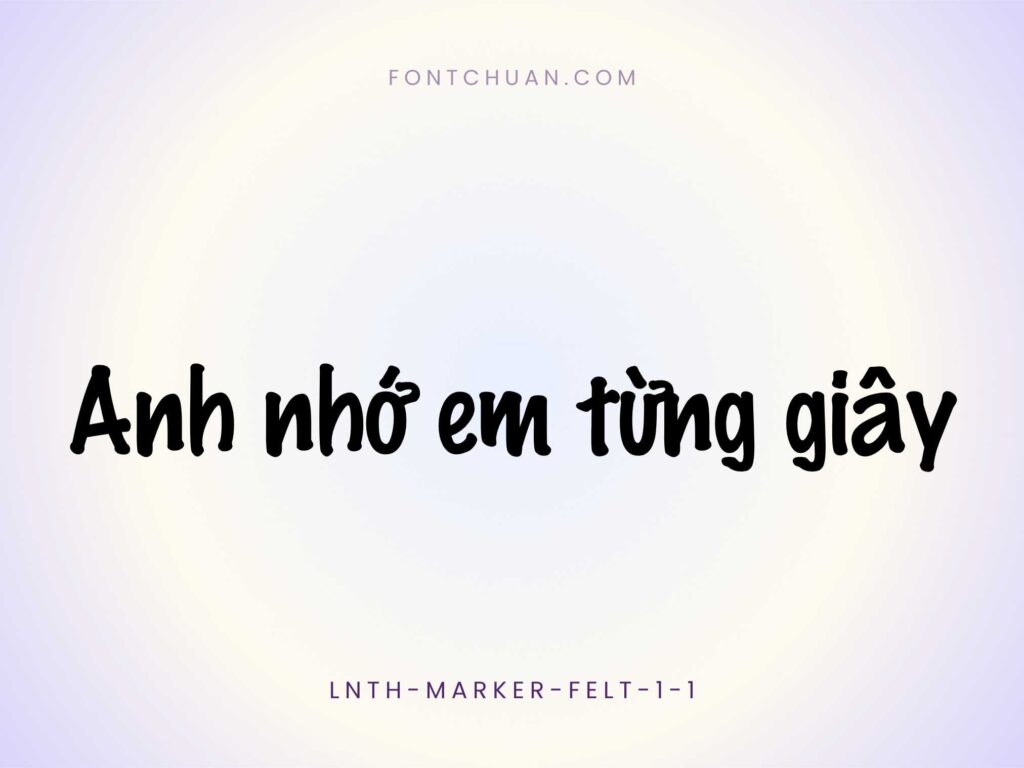
Font LNTH Marker Felt Việt Hóa
Font Marker Felt là một font chữ viết tay mang phong cách năng động, được thiết kế mô phỏng các nét bút dạ viết trên giấy. Với đường nét đậm, hơi thô nhưng đầy cá tính, font này rất phù hợp cho các thiết kế mang tính sáng tạo, trẻ trung, hoặc các nội dung cần sự nổi bật, vui tươi. Marker Felt thường được sử dụng trong thiết kế tiêu đề, quảng cáo, hoặc các ấn phẩm truyền thông sáng tạo
Phiên bản này đã được Việt hóa bởi LNTH, hỗ trợ đầy đủ tiếng Việt cùng hơn 50 ngôn ngữ khác, giúp người dùng dễ dàng ứng dụng trong thiết kế quốc tế. Font Marker Felt được các thành viên Font Chuẩn sưu tầm và đăng tải nhằm cung cấp một lựa chọn phù hợp cho những ai muốn sử dụng kiểu chữ năng động, phá cách
Về đặc điểm thiết kế, Marker Felt có độ dày lớn, đường nét không quá gò bó, tạo cảm giác tự nhiên như chữ viết tay thực tế. Font này đặc biệt thích hợp để sử dụng trong các tiêu đề lớn, thiết kế poster, banner, nhãn dán hoặc các sản phẩm liên quan đến trẻ em, giáo dục
Font Marker Felt được ứng dụng rộng rãi trong các sự kiện như lễ hội, sinh nhật hoặc các chiến dịch quảng cáo sáng tạo. Nó phù hợp với nhiều ngành nghề như quảng cáo, giáo dục, bất động sản, công nghệ